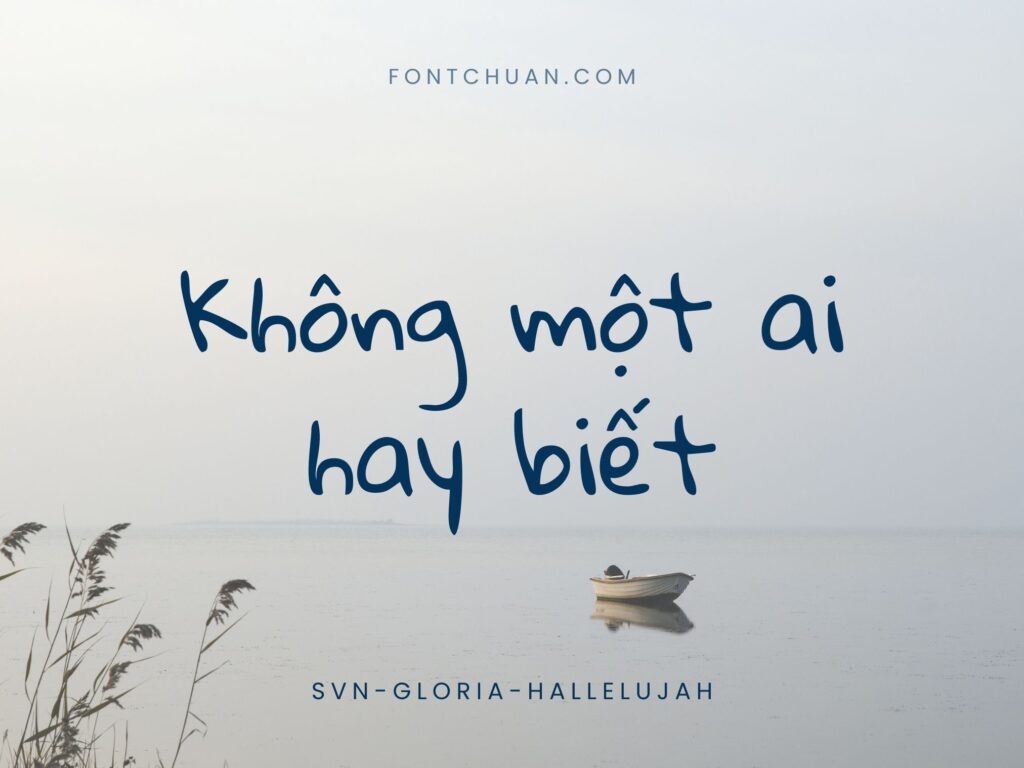
Font SVN Gloria Hallelujah Việt Hóa
Tác giả Font: Kimberly Geswein
Font SVN Gloria Hallelujah là phiên bản Việt hóa của kiểu chữ Gloria Hallelujah, được thực hiện bởi Styleno.1 Fonts. Gloria Hallelujah là một kiểu chữ viết tay vui nhộn, dựa trên nét chữ của một học sinh trung học Hàn Quốc, mang phong cách truyện tranh và tạo cảm giác thân thiện, tự nhiên. Font này thích hợp cho nhiều mục đích sử dụng khác nhau, từ thiết kế thiệp mời, tiêu đề đến các ấn phẩm truyền thông.
SVN Gloria Hallelujah lý tưởng cho các dự án thiết kế yêu cầu sự vui tươi và sáng tạo, như thiệp mời, tiêu đề, bao bì sản phẩm và các ấn phẩm quảng cáo. Các ngành nghề như giáo dục, ẩm thực và spa có thể tận dụng font này để tạo điểm nhấn trong thiết kế. Ngoài ra, font cũng thích hợp cho các sự kiện như Tết, Giáng sinh, Sinh nhật và các lễ hội khác.